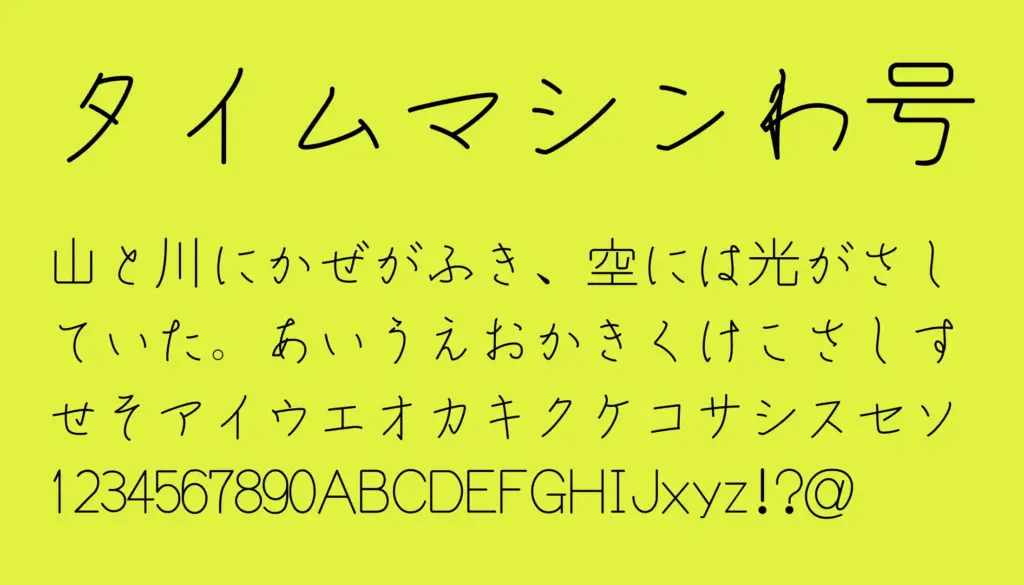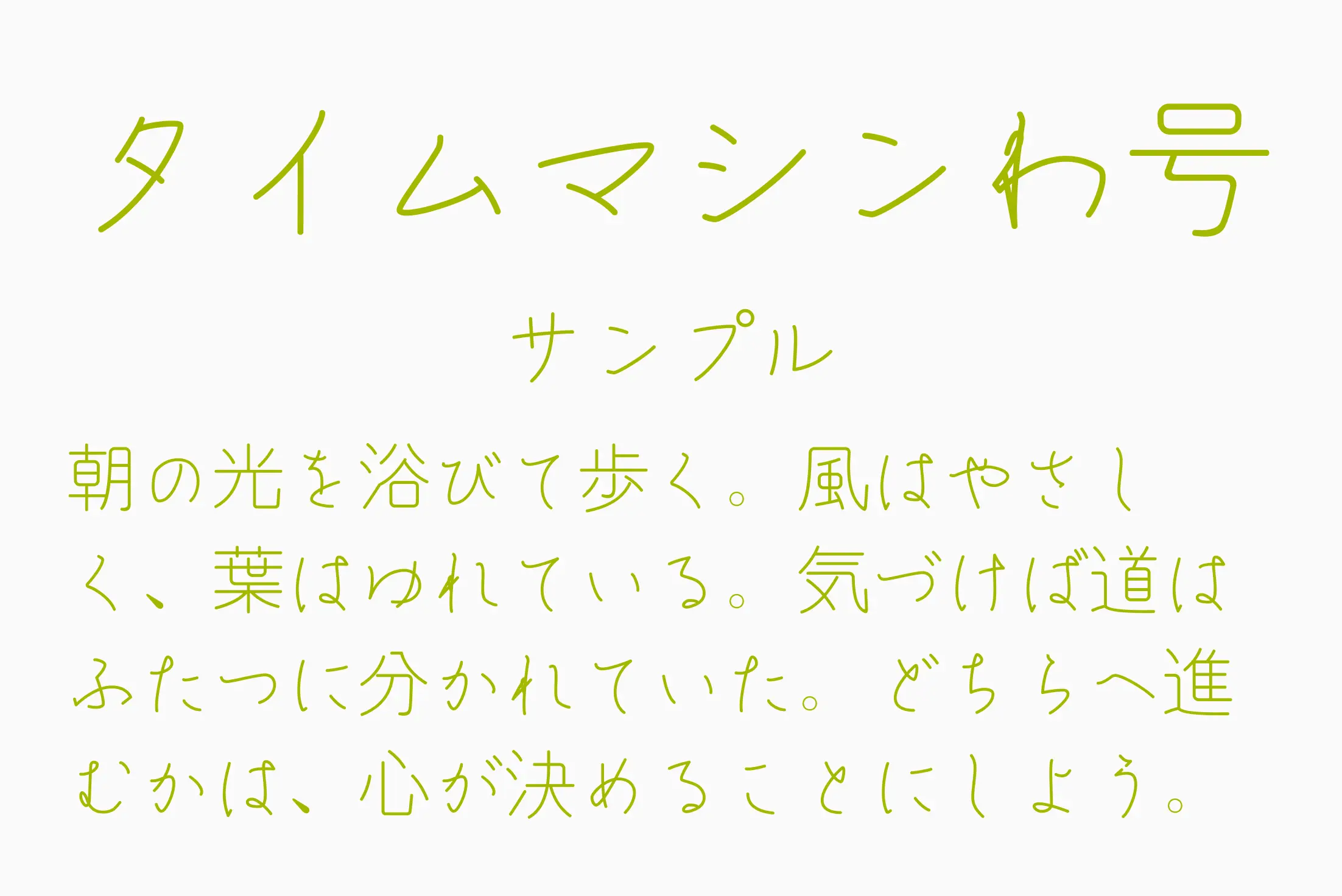
昭和レトロな活字感と、ざらっとした印刷の風合いを再現した、独特な味わいのある日本語フォントです。古い新聞や雑誌の見出しを思わせるような、懐かしくも力強い骨格とインクのにじみ表現が特徴。筆圧の強弱や微妙なかすれがデザインとして活かされており、タイトル・チラシ・イベントポスター・レトロ系動画サムネイルなどに最適。
タイムマシンわ号